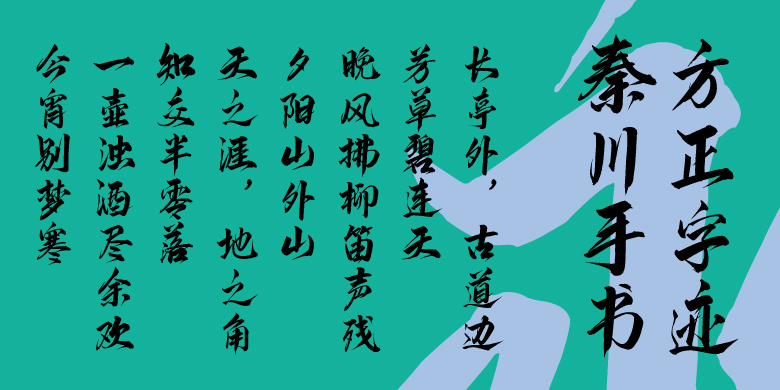
方正字迹-秦川手书
程东方
行楷、常规书写·毛笔
该款字保留行书的字形结构,保留笔画之间的连笔,在收笔的时候不内收而是外放,因此形成在章法之内,却充满了张力。本款字的笔画都采用三角的结构,当笔画有撇捺的笔画时,配合饱满的曲线,从粗到细的三角笔触结构,让字形视觉上更有呼吸感,强对比关系让视觉上更丰富。有别于传统的顿笔,这款字的顿笔加强,切转折果断,保持锋利的笔峰,让字形看起来更加锐利,在多字组合的时候气势感、力度都非常出挑。